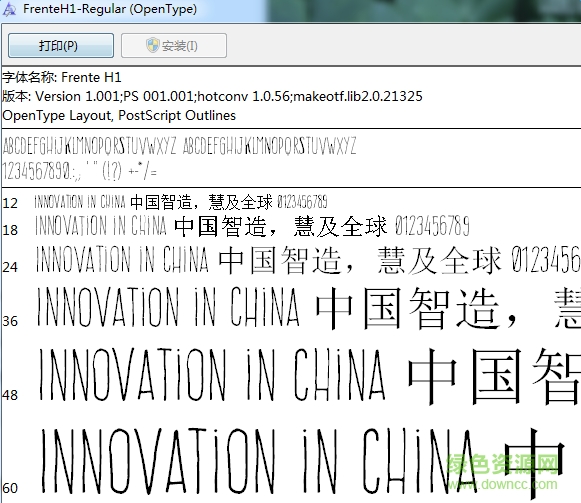
frenteh1字體是一款應(yīng)用個設(shè)計(jì)行業(yè)的英文個性字體,該字體可以廣泛應(yīng)用于廣告設(shè)計(jì)、宣傳海報(bào)、ppt、影視制作以及任何使用文字的領(lǐng)域,有需要的朋友可以免費(fèi)下載收藏。
frenteh1字體是一款英文字體庫中的個性字體嗎,該字體的形體纖細(xì),顯得比較秀氣,有需要的朋友可以來綠色資源網(wǎng)下載使用!